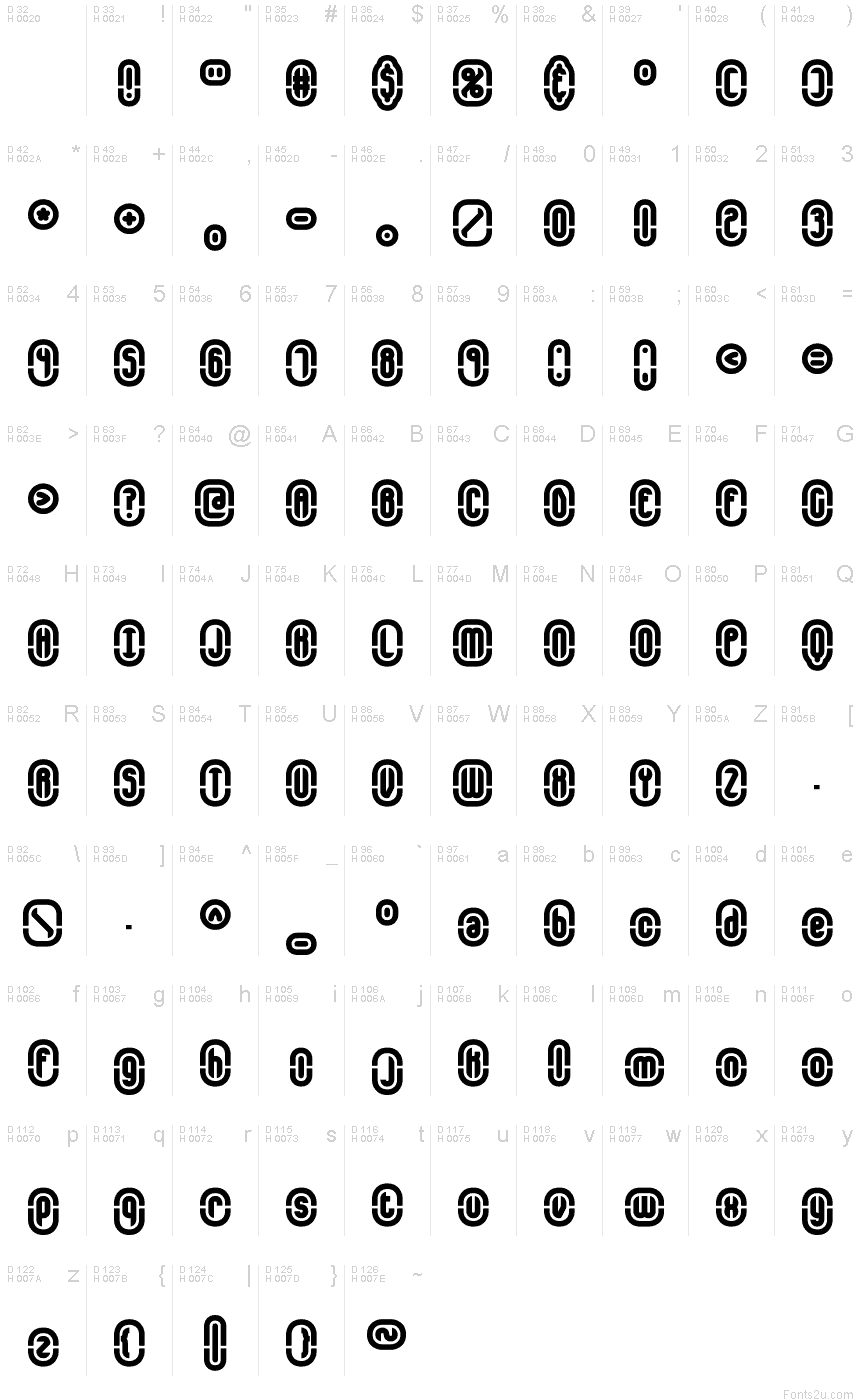
Encapsulate od ÆNIGMA FONTS to darmowy, utrzymany w stylistyce groovy krój displayowy o wyrazistym, dwuwarstwowym charakterze. Grube, czarne kontury otaczają miękkie, zaokrąglone litery, a białe wypełnienie tworzy wbudowany efekt bąbelków, przypominający tłoczenie. Rytm jest energiczny, ale kontrolowany, dzięki czemu napisy wyglądają, jakby unosiły się w łagodnej, retro chmurce, zamiast nachalnie domagać się uwagi.
Dzięki Encapsulate Twoje nagłówki przyciągną wzrok na ulotkach imprezowych, plakatach festiwalowych, okładkach płyt, zabawnych logotypach, naklejkach czy odważnych grafikach do mediów społecznościowych. Ten darmowy font najlepiej sprawdza się w dużych rozmiarach, gdzie jego masywne kontury i wyraziste linie mogą w pełni wybrzmieć. W przypadku tekstu głównego zestaw go z czystym, geometrycznym krojem bezszeryfowym, aby zapewnić czytelność układu, podczas gdy Encapsulate zadba o zabawę.
Encapsulate BRK